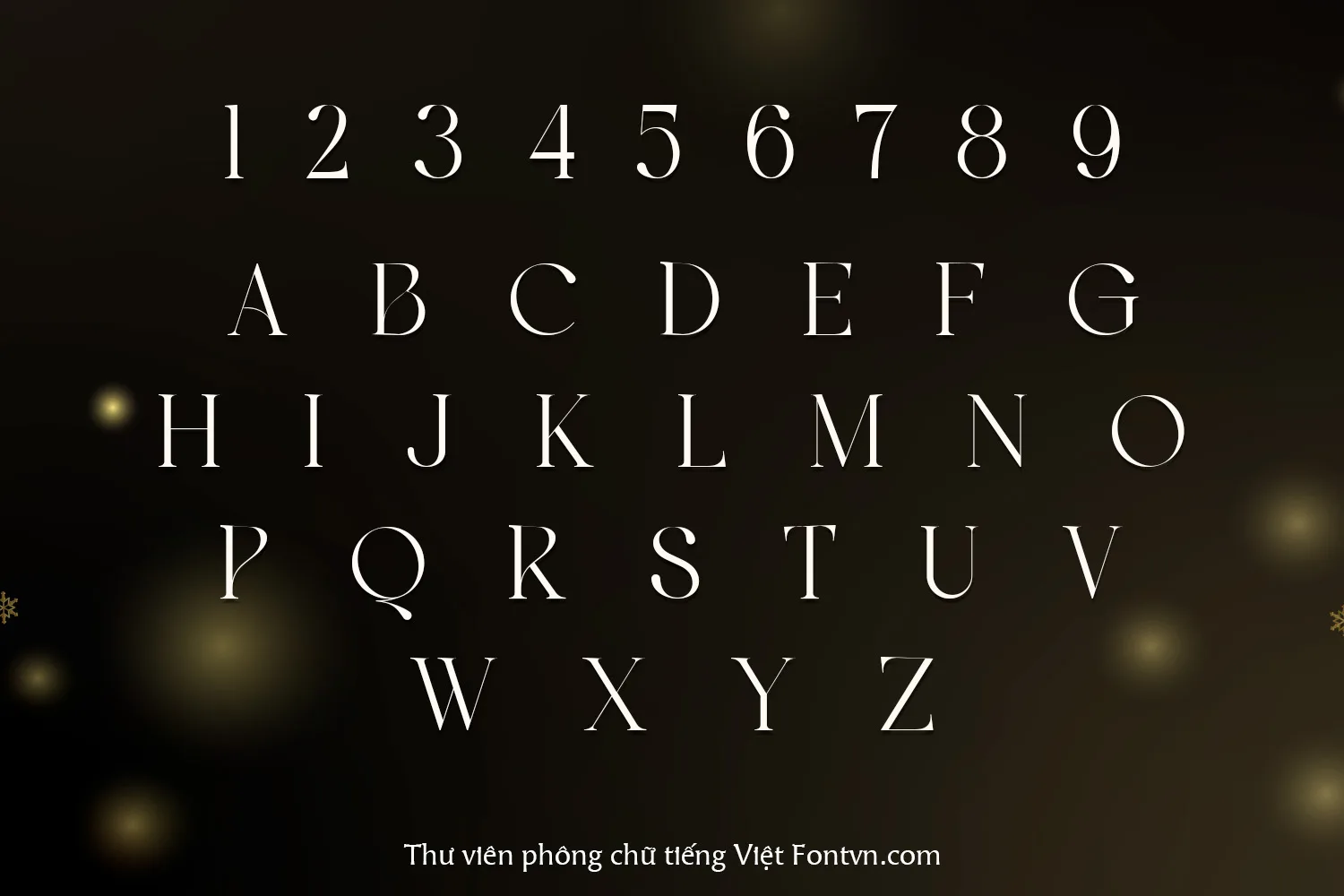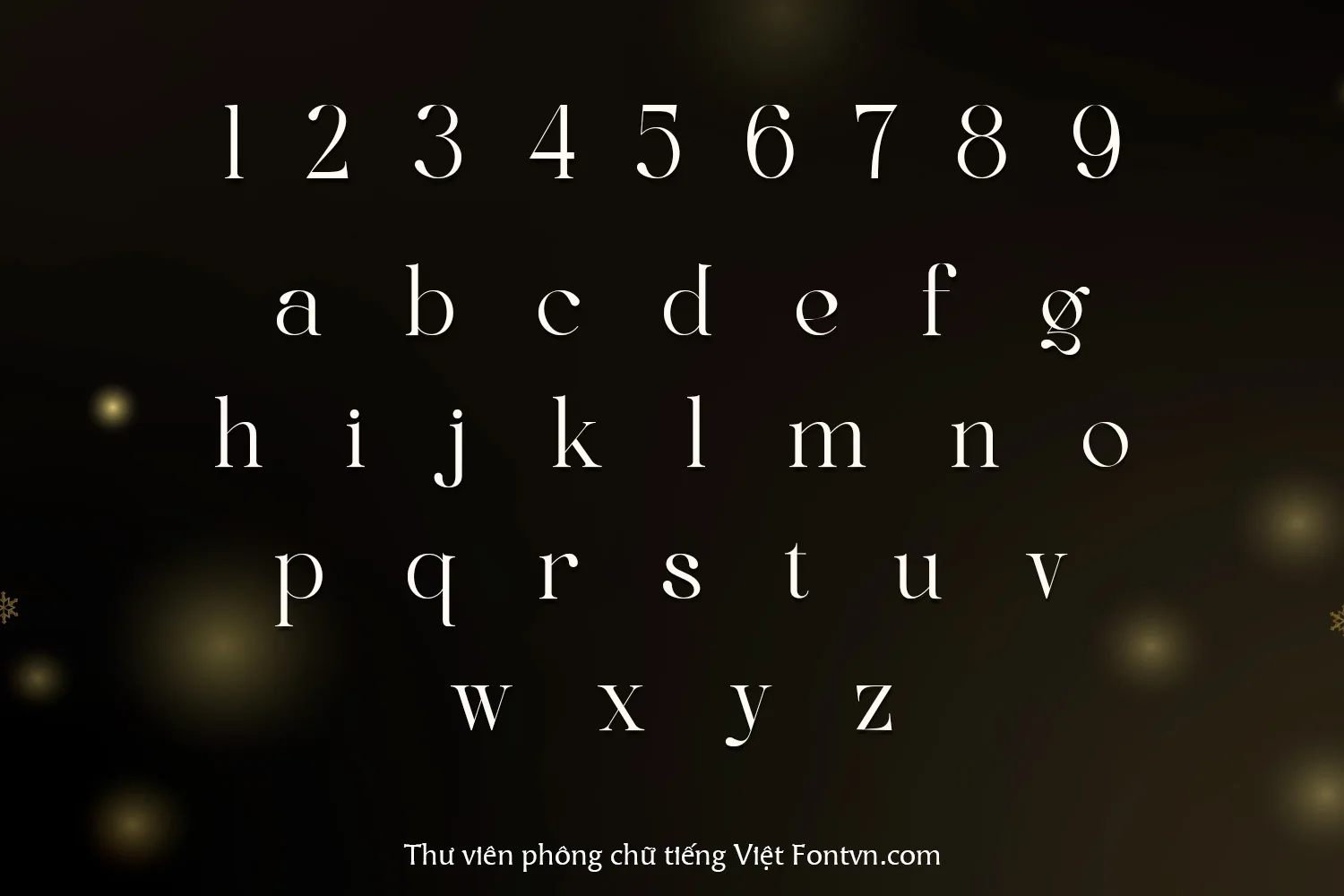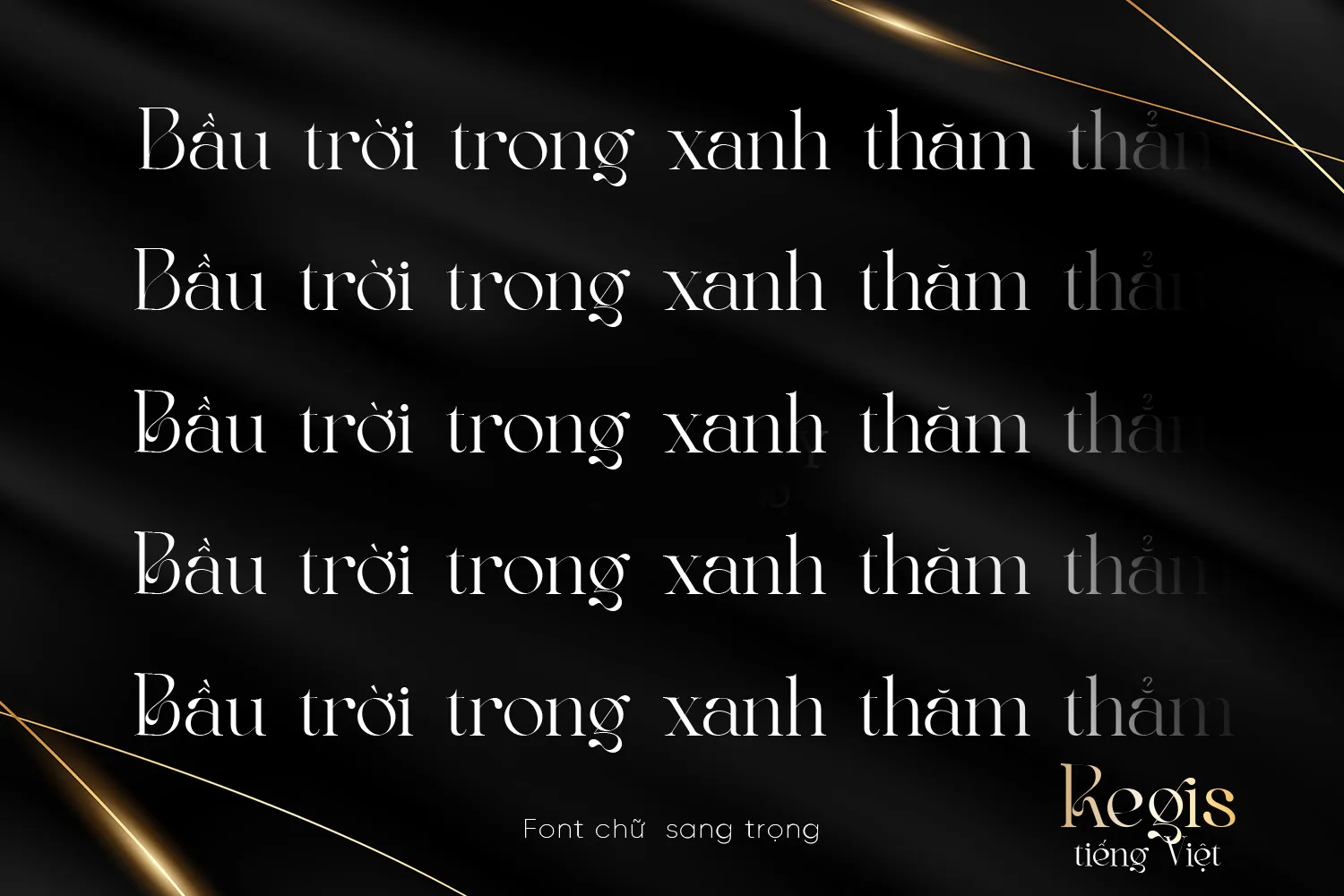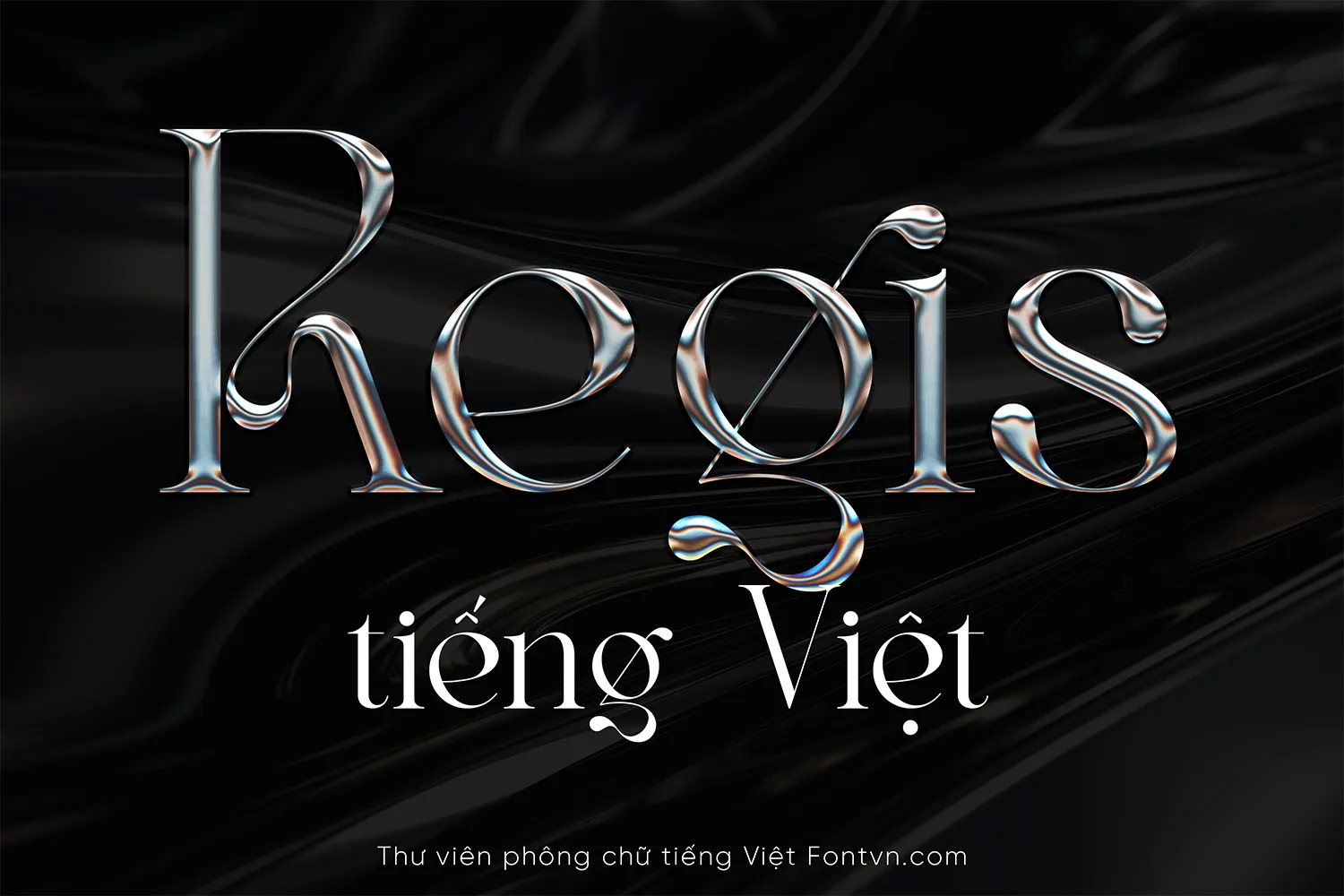
DVN Regis tiếng Việt – Font Serif Cao Cấp Cho Branding & Thiết Kế Thời Trang
DVN Regis là phông chữ serif mang phong cách editorial sang trọng, được Việt hóa đầy đủ với hệ thống dấu tiếng Việt tối ưu. Font sở hữu độ tương phản nét cao, các đường cong mềm mại cùng ligature và swash tinh tế, tạo nên vẻ đẹp đẳng cấp cho logo, branding, thời trang, mỹ phẩm, thiệp cưới, tạp chí và các dự án thiết kế cao cấp. Với khả năng hiển thị sắc nét và cân đối, DVN Regis là lựa chọn hoàn hảo cho những ai đang tìm kiếm một kiểu chữ serif hiện đại nhưng vẫn giữ được nét cổ điển đầy cuốn hút.